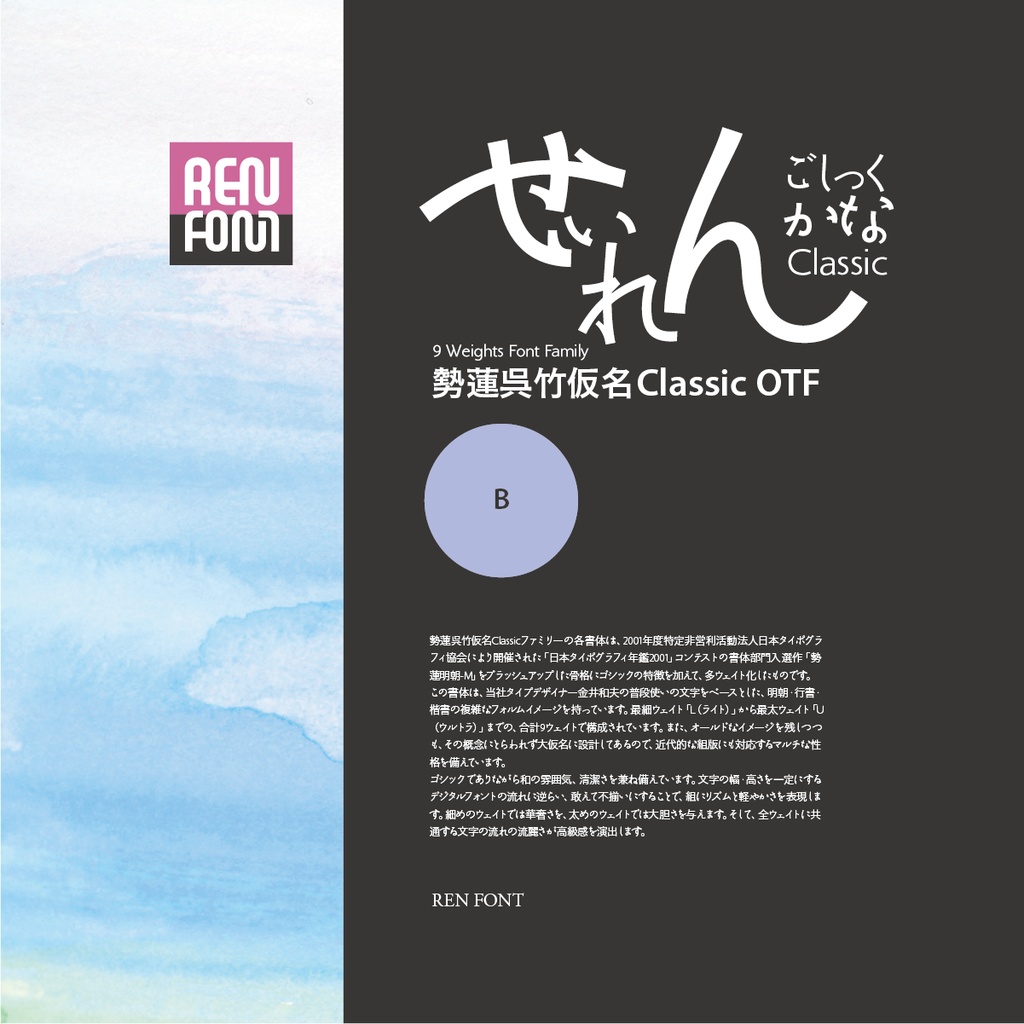
●ゴシックを感じさせない優雅さ 勢蓮呉竹仮名Classic 9ウェイトファミリー / OpenType
ゴシックでありながら和の情緒、清潔さを合わせ持つ。
勢蓮呉竹仮名Classicファミリーの各書体は、2001年度特定非営利活動法人日本タイポグラフィ協会により開催された「日本タイポグラフィ年鑑2001」コンテストの書体部門入選作「勢蓮明朝-M」をブラッシュアップした骨格にゴシックの特徴を加えて、多ウェイト化したものです。 この書体は、当社タイプデザイナー金井和夫の普段使いの文字をベースとした、明朝・行書・楷書の複雑なフォルムイメージを持っています。最細ウェイト「L(ライト)」から最太ウェイト「U(ウルトラ)」までの、合計9ウェイトで構成されています。また、オールドなイメージを残しつつも、その概念にとらわれず大仮名に設計してあるので、近代的な組版にも対応するマルチな性格を備えています。 ゴシックでありながら和の雰囲気、清潔さを兼ね備えています。文字の幅・高さを一定にするデジタルフォントの流れに逆らい、敢えて不揃いにすることで、組にリズムと軽やかさを表現します。細めのウェイトでは華奢さを、太めのウェイトでは大胆さを与えます。そして、全ウェイトに共通する文字の流れの流麗さが高級感を演出します。
ウェイト
●All[フルウェイト] ●EL[エクストラライト] ●L[ライト] ●R[レギュラー] ●M[ミディアム] ●DB[デミボールド] ●B[ボールド] ●EB[エクストラボールド] ●H[ヘビー] ●U[ウルトラ]